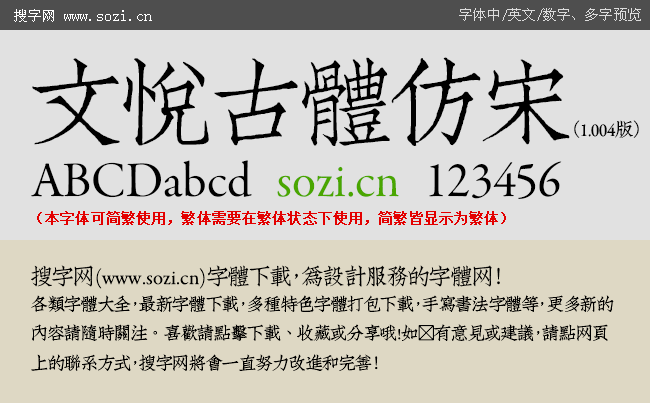
文悅古體仿宋
搜字網給大家提供一款文悅古體仿宋中文字體下載。文悅古體仿宋字體基于聚珍仿宋頭號方體字原件制作,聚珍仿宋頭號方體字是在民國期間使用非常廣泛的字體,文悅古體仿宋字體保留了該字體的美觀特性。文悅古體仿宋除對部分文字作了修繕并增補了缺失的現代常用字外,還專門設計了多項高級特性,以使用戶可以方便地利用該計算機字體作出如同古典書籍般的排版效果。可用于排版設計、海報設計、包裝設計等廣告設計場合。